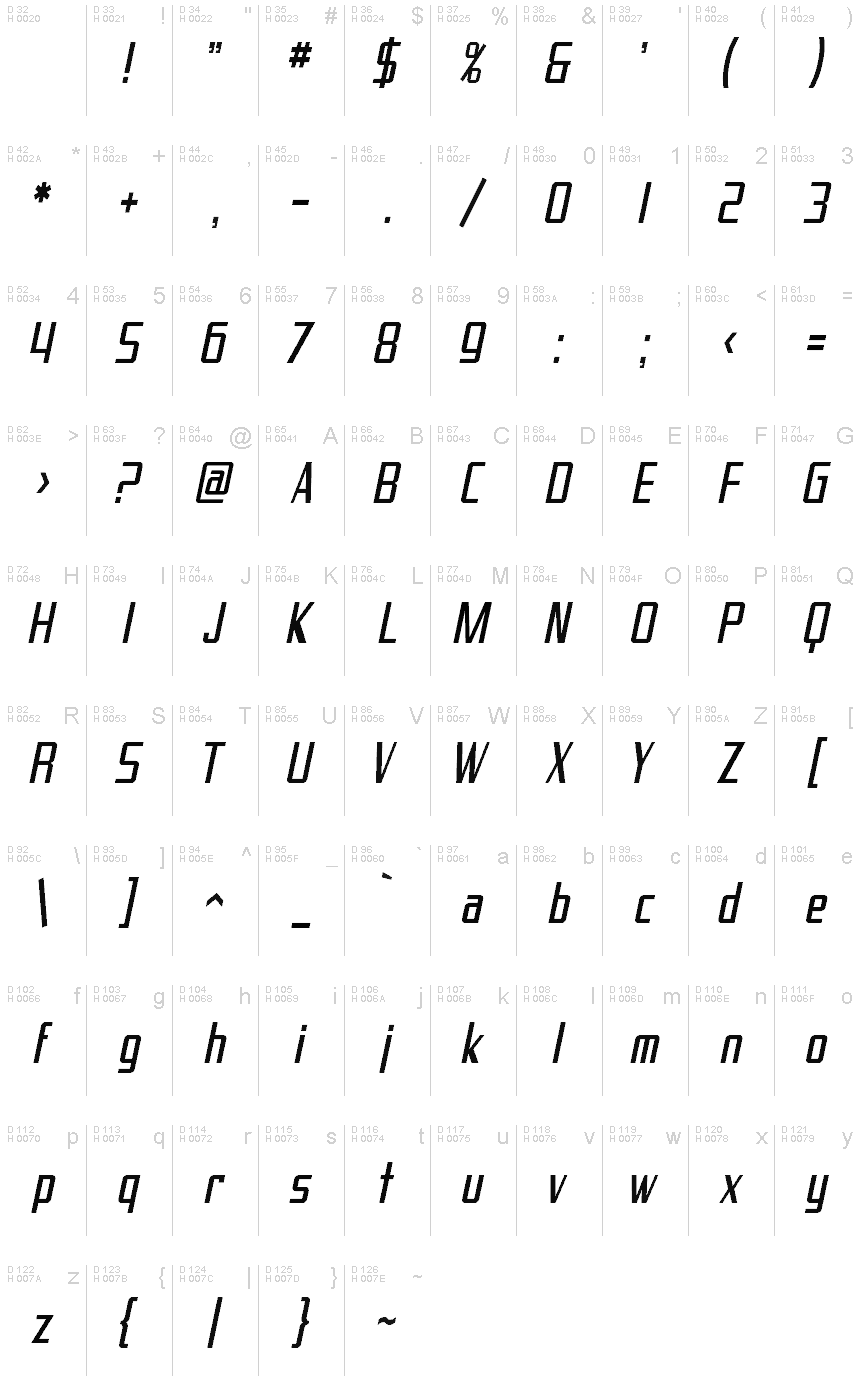
SF Proverbial Gothic Condensed Oblique
SF Proverbial Gothic Condensed Oblique è un carattere distintivo della famiglia SF Proverbial Gothic, meticolosamente creato dalla ShyFonts Type Foundry. Questo font display vanta uno stile techno che fonde modernità e note gotiche, creando un'estetica intrigante che cattura l'attenzione. Grazie alla sua leggerezza e alla larghezza extra-condensata, emana un aspetto elegante e sofisticato.
L'inclinazione obliqua aggiunge dinamismo al suo carattere, rendendolo particolarmente efficace per progetti che richiedono un senso di movimento o un approccio all'avanguardia. Il suo mix unico di elementi gotici tradizionali e design contemporaneo lo rende ideale per il branding, l'editoria e i media digitali che mirano a lasciare un segno.
Che si tratti di startup tecnologiche, brand di moda o campagne pubblicitarie all'avanguardia, SF Proverbial Gothic Condensed Oblique offre versatilità e un impatto visivo straordinario. La sua personalità unica può aiutare a elevare i vostri progetti creativi a nuovi livelli.